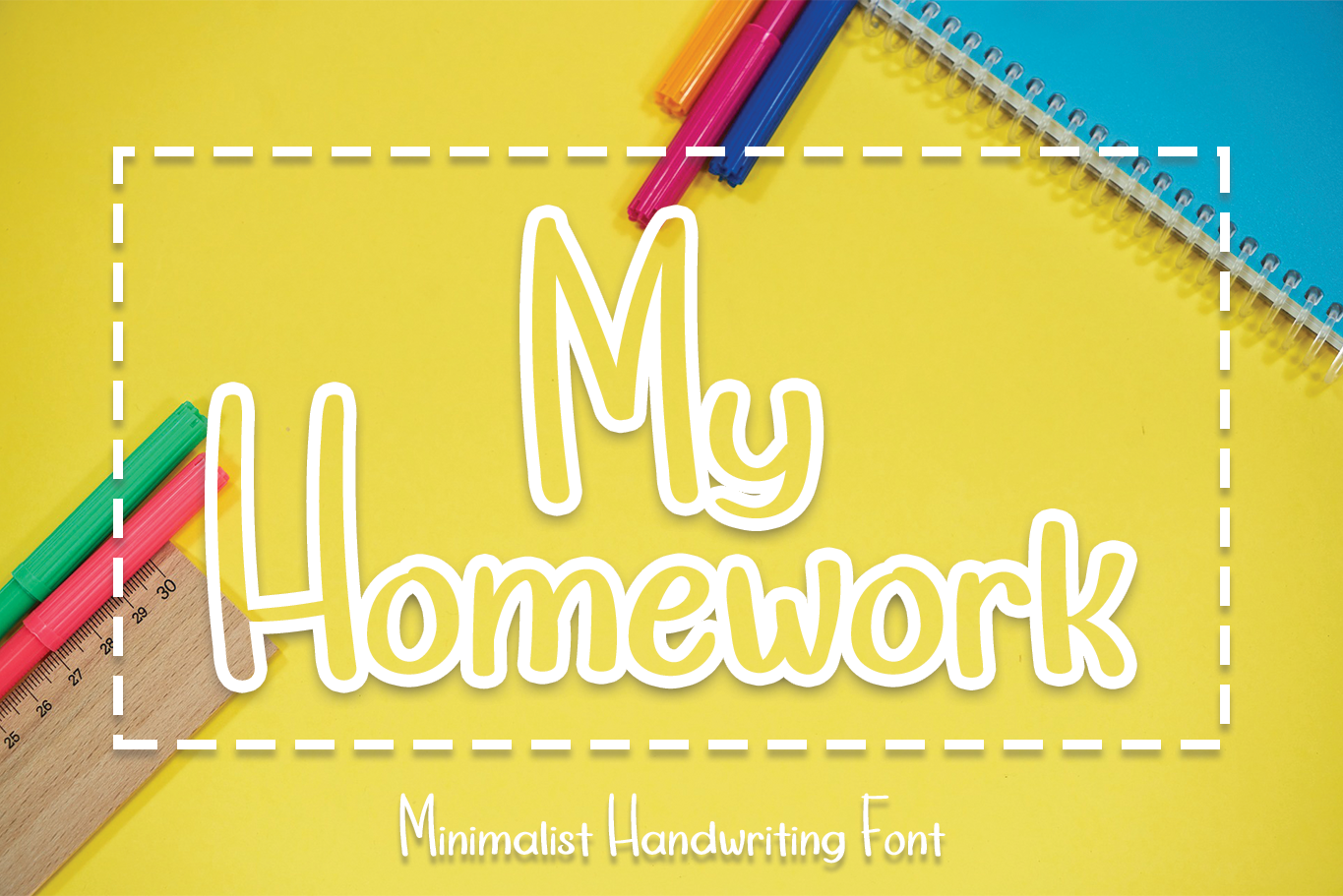
My Homework Font – Download Grátis
Esta é uma fonte escrita à mão com um aspecto autêntico e descontraído. Ela tem um toque amigável que certamente dará um ar pessoal e realista aos seus projetos gráficos. Para quem busca uma fonte leve e fácil de usar, o My Homework Font é perfeito. Sua aparência natural e encantadora irá enriquecer qualquer projeto, seja ele para cartazes educacionais ou anúncios lúdicos. Se você está procurando por uma fonte que traga um toque único e divertido aos seus designs, esta pode ser a escolha perfeita para agregar personalidade à sua arte digital de maneira encantadora. Ela será um dos aliados indispensáveis no seu arsenal criativo, garantindo resultados imediatamente impactantes e memoráveis.